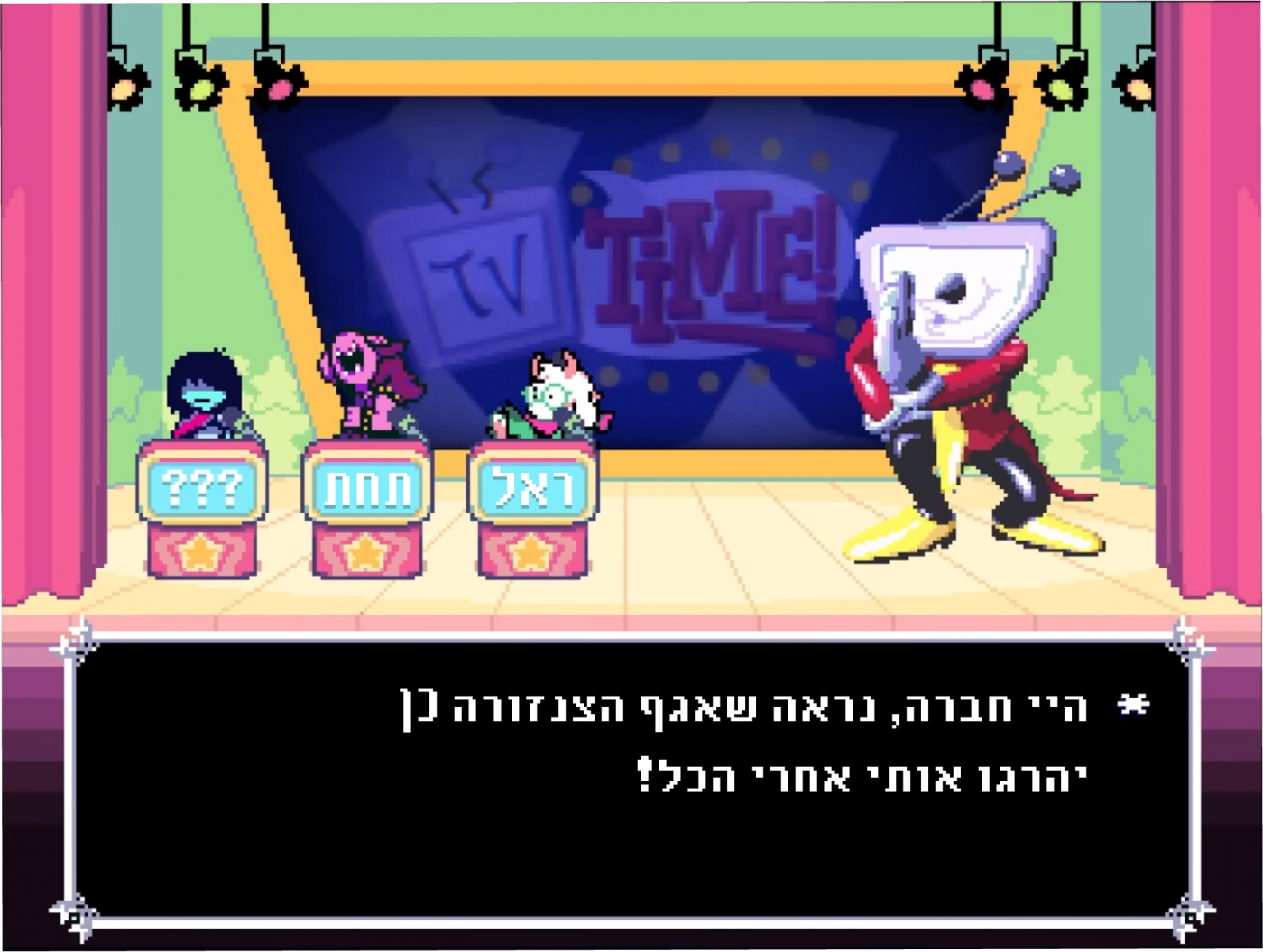
• פונט שנועד לשימוש יחד עם פונט אנדרטייל שהכנתי https://fontstruct.com/fontstructions/show/2752684/ndrtyyl . הוא אמור לשמש למילים שבאנדרטייל נכתבות באפר קייס להדגשה.
הגופן הזה נועד להדגיש מילים מסויימות שבמקור הן אותיות גדולות באנדרטייל